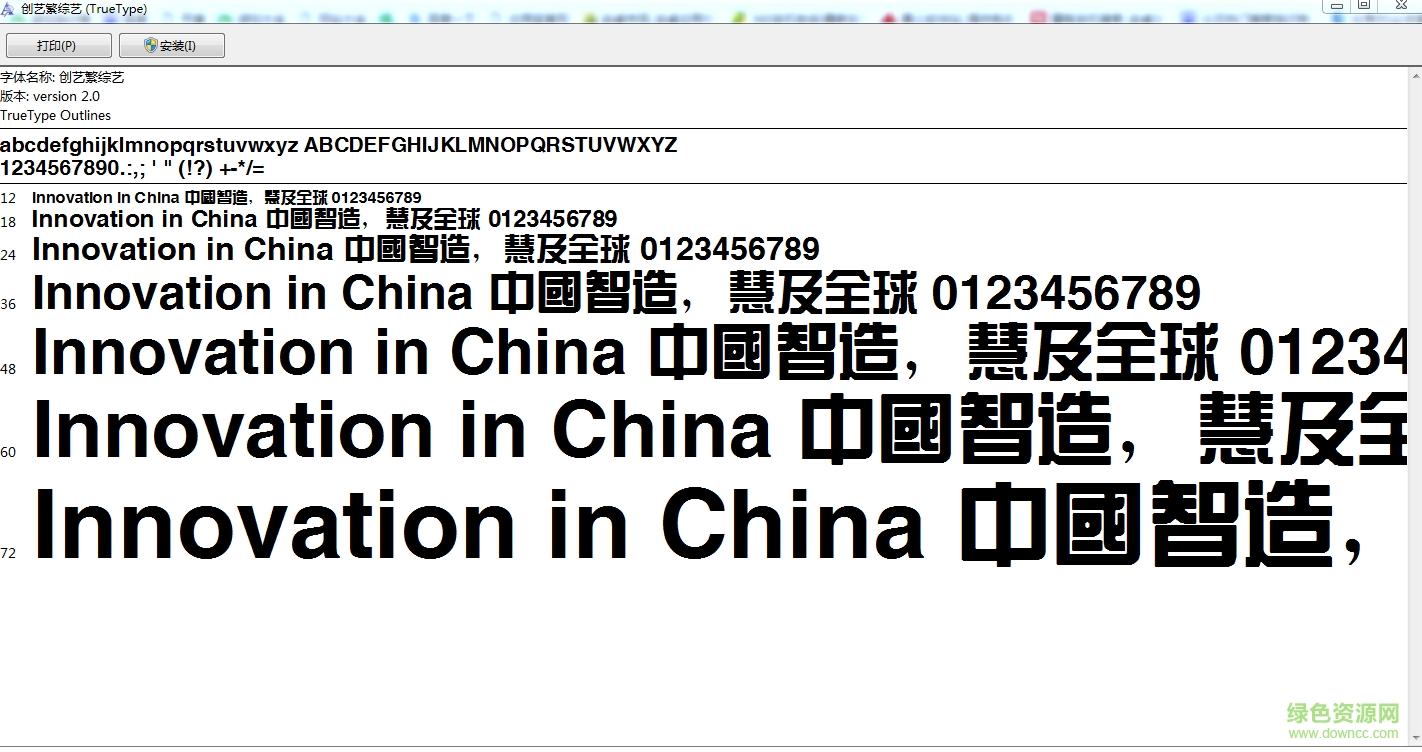
ctzongyisf(創(chuàng)藝繁綜藝)字體是一款粗壯大氣的繁體字體,筆致遒勁,古樸有型,繁體設(shè)計(jì)非常有藝術(shù)感,看上去韻意深長(zhǎng),非常適合進(jìn)行繁體藝術(shù)字創(chuàng)作的朋友使用,而且在本站下載的字體都是可以永久免費(fèi)使用的哦,需要的朋友快來(lái)下載吧!
ctzongyisf字體是一款非常有特色的藝術(shù)字體,可用于商業(yè)字體、企業(yè)名稱(chēng)、產(chǎn)品包裝、出版圖書(shū)等行業(yè),